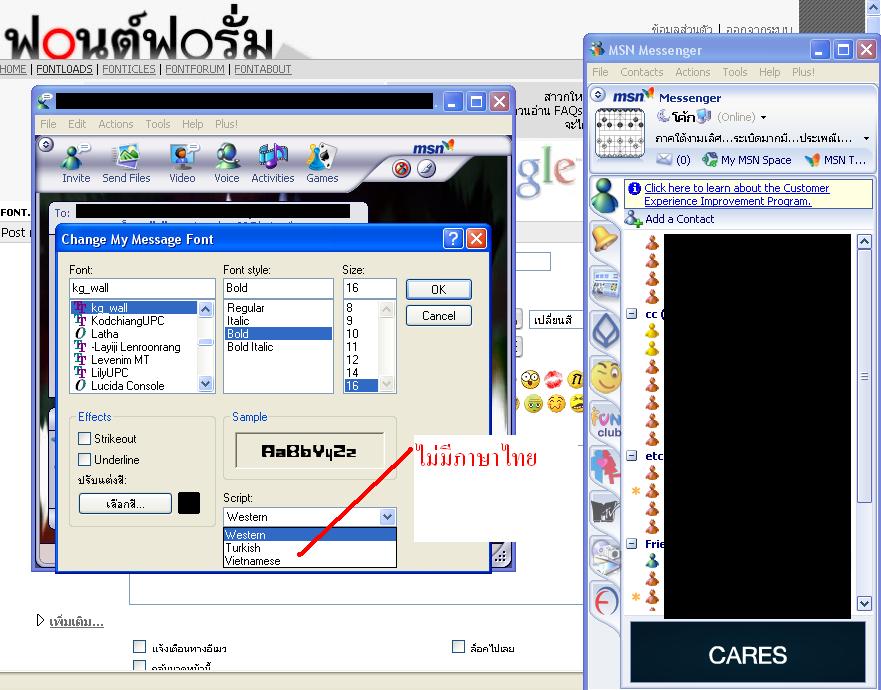
ทำไมพิมภาษาไทยไม่ได้ครับ
ผมติดตั้งฟอนต์ kg_wall ไปแล้วแต่ไม่สามารถพิมพ์พอนต์นั้นเป็นภาษาไทยได้เพราะอะไรครับ
ที่ให้ทดลองพิมมันเป็นภาษาไทยนิครับ :09: :09: :09:
ใช้กับโปรแกรมอะไรครับ วานบอกหน่อย?
อ้อ แล้วลองเปลี่ยนเป็นฟอนต์อื่นดูว่าเป็นอาการเดียวกันหรือเปล่า
Msnครับ
ปกติมันจะมีให้เลือกไทยครับ
นี่ครับอันปกติ
(แอบถาม : แล้วเวลาคุยเอ็มกัน อีกฝ่ายจะเห็นเหมือนเราด้วยเหรอครับ )
ห้าม
นำฟอนต์นี้ไปใช้กับ MSN เนื่องจากว่าถึงเครื่องคุณมันจะแสดงผล
แต่เครื่องของคู่สนทนา มันก็จะไม่แสดงนะครับ เพราะคู่ของคุณเขาไม่มีฟอนต์ตัวนี้
ตามนั้นครับ
เปลี่ยนไปก็ไม่เห็นผล นอกจากจะทำให้มันอ่านยากขึ้น
ทำไมผมใช้ฟอนต์อื่นแล้วเพื่อนก็เห็นแสดงผลปกติล่ะครับเพื่อนผมก็ไม่เคยโหลดฟอนต์อื่นๆเพิ่มด้วย
บางทีผมเปลี่ยนฟอนต์เพื่อนมันยังบอกว่าอันเดิมสวยกว่า
ก็ใช้อันเดิมต่อไปสิครับ
แต่Kg_wallมันเท่ กว่าอันเก่านิครับ
เพื่อนเขาเห็นเป็นฟอนต์ทื่อๆ ในเครื่องครับ
เช่น เห็นเป็น Times New Roman แต่ภาษาไทยเป็น Cordia ตัวจิ๋วๆ
เขาเลยบอกของเดิมดีกว่า